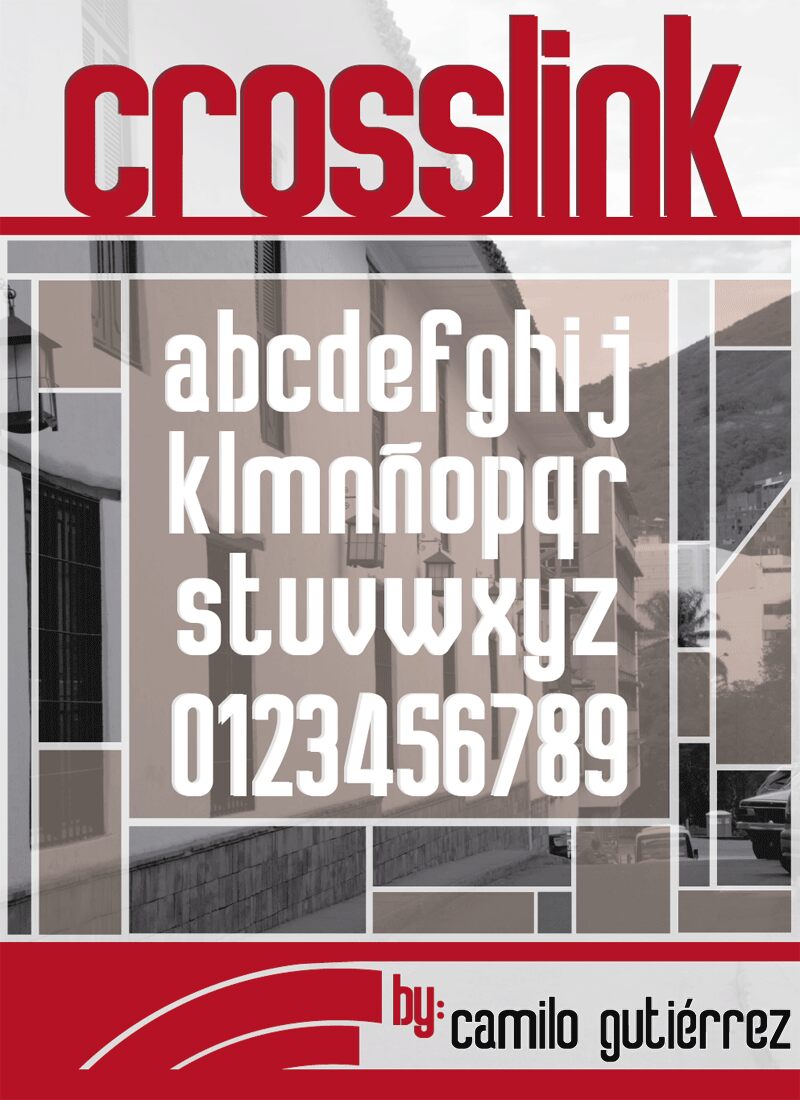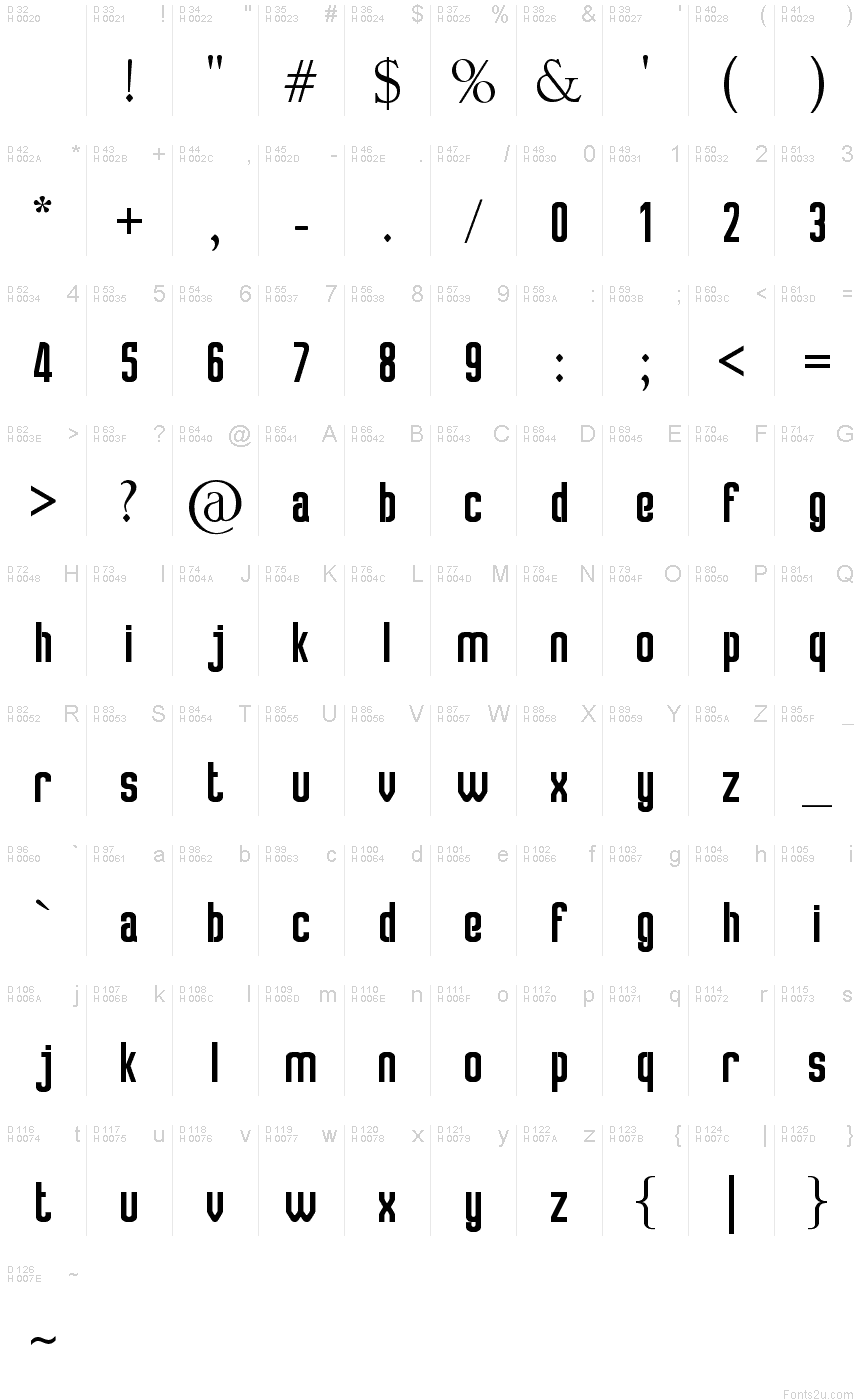
Crosslink
Esta fuente tipogrfica est inspirada en el Estilo Internacional Suizo, combinando de esta manera las caractersticas principales de este movimiento.